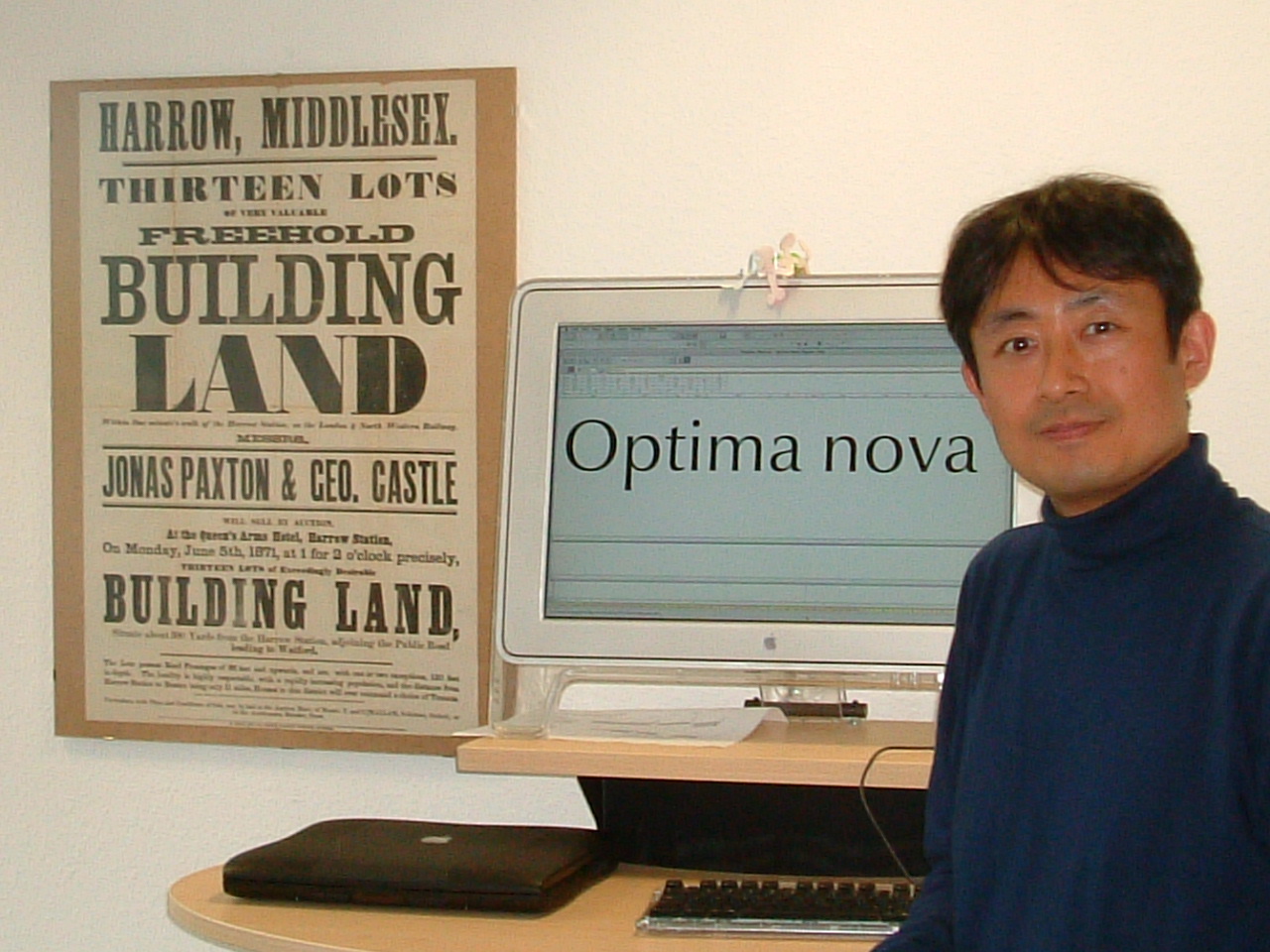
デザイナーなら誰でも一度は使ったことのある、あのオプティマが生まれ変わりました。
オプティマ (Optima) といえば Palatino と並んでドイツの書体デザイナーのヘルマン・ツアップ氏(1918〜)の代表的な書体デザインです。 誰もが知っていてどこでも目にする書体です。ただしTimes や Helvetica とは少し違い、高級な化粧品やレストランなど優雅さや高級感の欲しい時に使われる、気品のある書体です。ファッション雑誌を見てください。服の流行は目まぐるしく変わりますが、オプティマを使った広告を見かけないことはありません。
オプティマの最初のスケッチは1000リラ紙幣に描かれました。書体デザイナーのツアップ氏は1950年にフィレンツェを旅行中にたまたま立ち寄ったサンタ・クローチェで見つけた碑文に感銘を受け、その形を描き残すため紙を探しました。あいにく手もとに紙がなく、彼は紙幣にスケッチを書き残したのです。その後 ツアップ氏がドイツに戻って書体化のための慎重な可読性テストが行なわれ、1952年に最初の下描きを完成させました。
フーツラのようなサンセリフ体とボドニのような古典的なロ−マン体との中間の書体を開発したいという発想のもとにオプティマは制作されました。通常のサンセリフ体に見られる直線の連続からくる単調さを避けるために、画線は微妙なカーブを持たせています。これはオプティマ書体ファミリーに共通する特徴であり、これがオプティマのデザインの優雅さを際立たせます。オプティマの最初のスケッチから50年経って今回 Linotype Optima nova の名前でリデザインがなされ、デザイン的な妥協のないデジタル書体のオプティマが完成しました。
ヘルマン・ツアップ氏と、日本人書体デザイナーの小林章さんとの密接なコラボレーションによってオプティマ改刻の作業は進められ、すべての文字が作り直されました。スモール・キャップやオールドスタイル数字が追加され、新しいデザイン Optima nova Titling も加わりました。Optima nova Titling は大文字だけの書体で、特別な組み合わせの文字や合字が用意されており見出しやロゴなどにふさわしい書体です。
オプティマはもともと活字書体としてデザインされました。当時の大量の印刷に向いた自動鋳植機用の活字をつくるため、デザイン的に妥協をした部分が少なからずあったのです。
例えば小文字の f は寸詰まりのような形にならざるをえませんでした。そのデザインをデジタル書体の時代になってもそのまま使っていたのです。デザイナーのツアップ氏自身も以前のオプティマには不満がたくさんあると言っていたくらいです。市場に出ているデジタル書体のは多くても、プロが使うために時間をかけている良い書体はほんの一握りです。私自身もいろんな会社の欧文デジタル書体を購入して何度も驚かされた経験があります。
今回の改刻で、すべての文字がデジタル書体の時代にふさわしくデザインされました。
このプロジェクトの間、ツアップ氏は多い時は週に二日ライノタイプ・ライブラリ社の私のオフィスに訪れ、ツアップ氏が私の隣に座って指示を出し、私はコンピュータに向かってその場でデザインをするという共同作業をすすめてきたのです。ツアップ氏はもちろんすべての文字に目を通しており、彼が望んでいたとおりのオプティマを作ることができました。古い書体の単なる焼き直しでないことは、プロの方にはわかっていただけると思います。現にアメリカの著名なブックデザイナーから詩集を組んでみたらたいへん良かったとの反響がかえってきています。